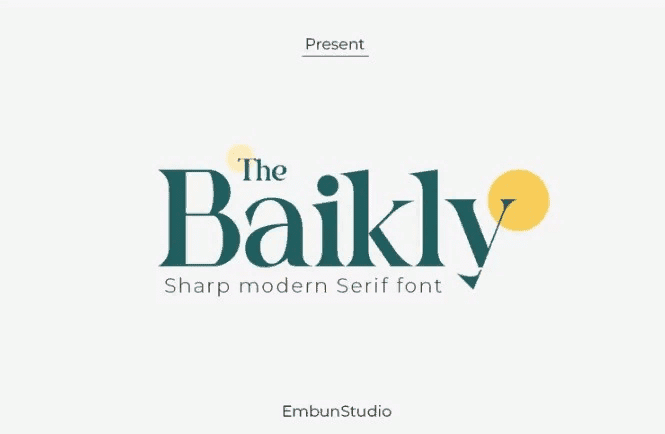
Название: The Baikly Font (2021)
Шрифт Baikly Serif вдохновлен озером Байкал в России!
Самое глубокое и древнее озеро, но дающее прекрасный вид и радующее глаз.
Надеюсь, этот шрифт сделает ваш любой проект более красивым и порадует глаз каждого, кто его увидит